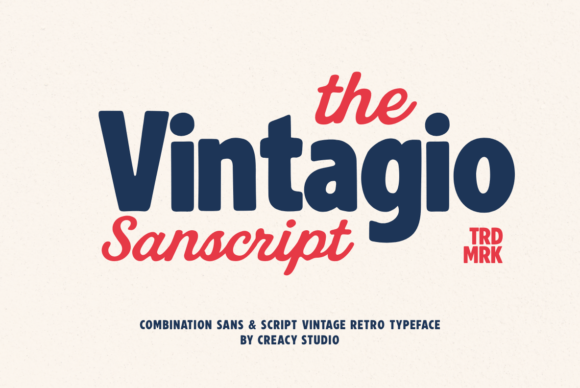
Vintagio Sanscript Duo Font
Att hitta rätt designelement kan vara utmanande, men Vintagio Sanscript Duo Font erbjuder en exceptionell samling som omedelbart lyfter ditt arbete.
Oavsett om du skapar POD-produkter (Print on Demand), bröllopsinbjudningar eller grafik för sociala medier, är Vintagio Sanscript Duo Font ett perfekt val.